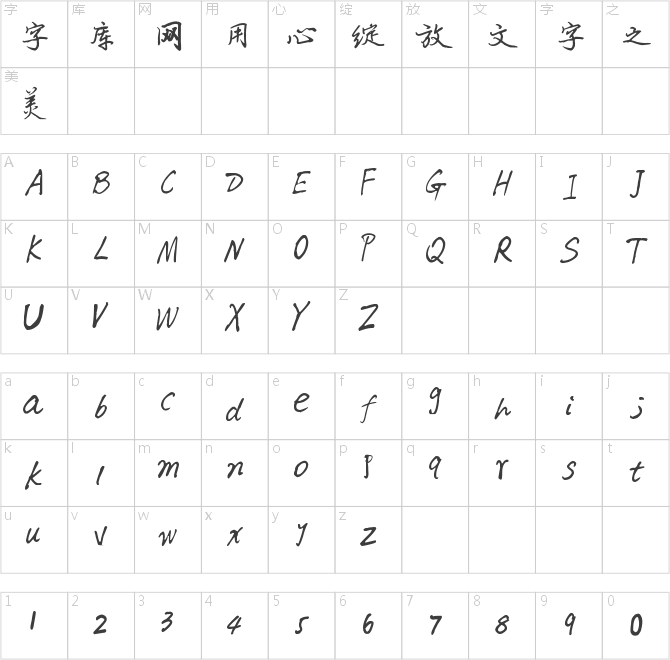
漢呈波波硬行(精細(xì)版) 詳情頁
字體名稱: 漢呈波波硬行(
漢呈波波硬行(精細(xì)版)
漢呈波波硬行(精細(xì)版)字體字庫是一款讓人賞心悅目、百看不厭的中文字體,適合各類廣告和產(chǎn)品包裝設(shè)計應(yīng)用,字體大小3.78MB,格式為ttf字體,上傳用戶是漢呈字庫,作者/版權(quán)方為漢呈字庫